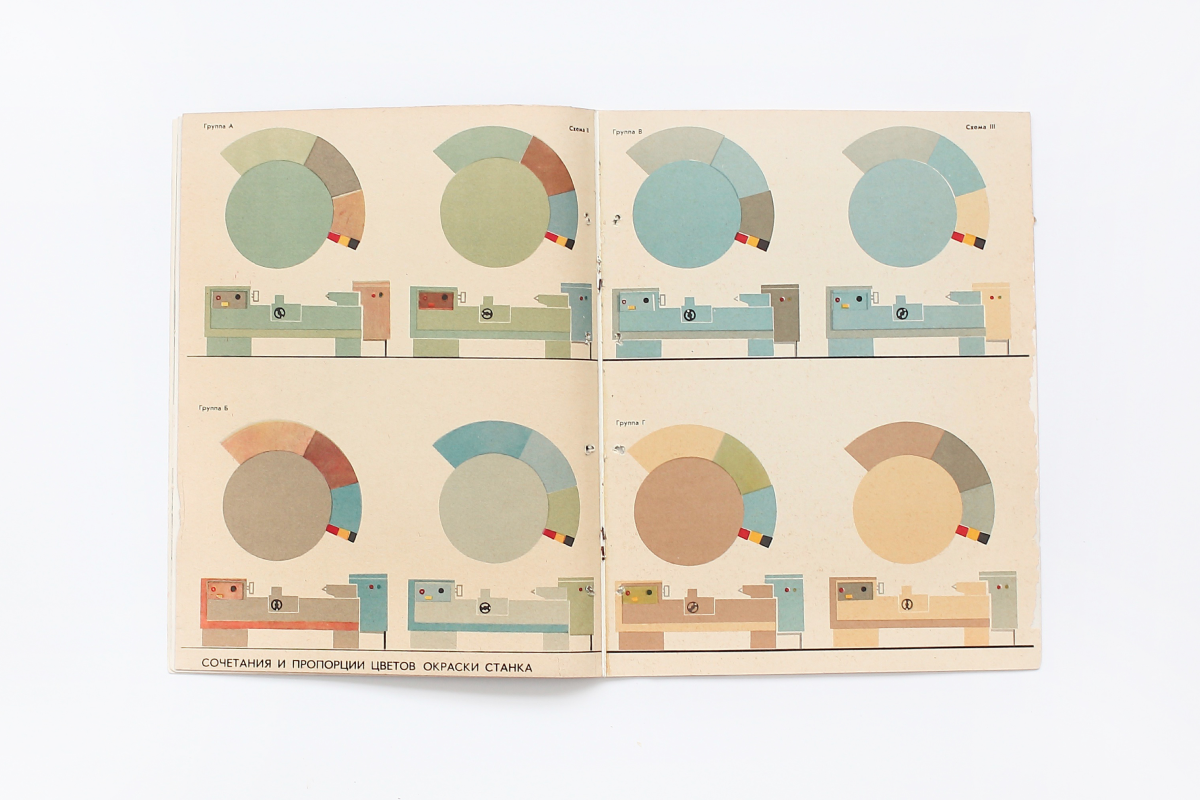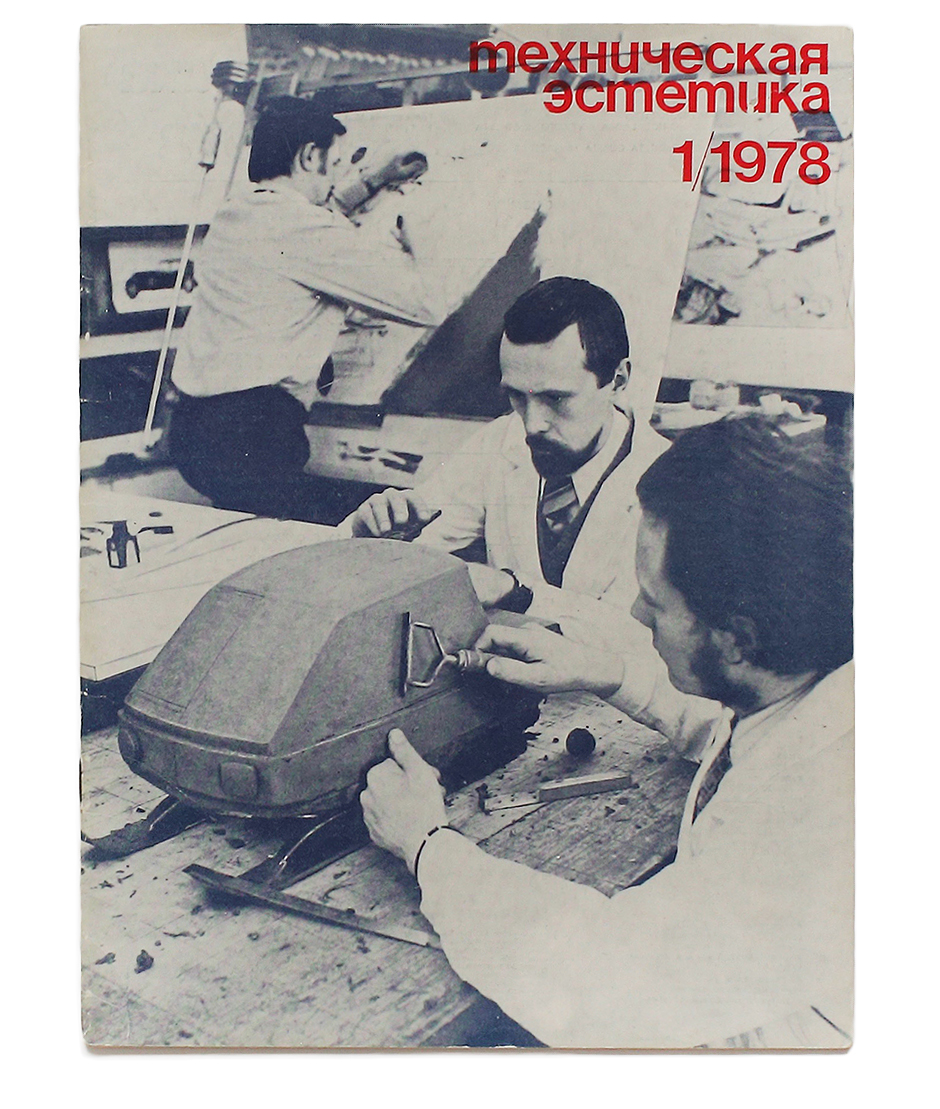
Техническая эстетика: эпизоды из жизни легендарного бюллетеня
ы живём во вре­ме­на, пе­ре­на­сы­щен­ные ин­фор­ма­ци­ей, но при этом очень мно­гое про­хо­дит ми­мо на­ше­го вни­ма­ния. К при­ме­ру, со­вет­ский ди­зайн. «Зверь», до сих пор эк­зо­ти­че­ский и ма­ло­изу­чен­ный не толь­ко в ми­ре, но и в со­вре­мен­ной Рос­сии.
Ис­кус­ство­вед Сер­гей Се­ров как-то за­ме­тил: «В Со­вет­ском Со­ю­зе бы­ли ди­зай­не­ры, а ди­зай­на не бы­ло». Фра­за кра­си­вая, но мне ка­жет­ся, бы­ли и ди­зай­не­ры, и ди­зайн. Бы­ла це­лая ор­га­ни­за­ция, за­ни­ма­ю­ща­я­ся про­бле­ма­ми раз­ви­тия ди­зай­на, — Все­со­юз­ный на­уч­но-ис­сле­до­ва­тель­ский ин­сти­тут тех­ни­че­ской эсте­ти­ки (ВНИ­ИТЭ). Сто­ит от­ме­тить, что офи­ци­аль­но в Стра­не Со­ве­тов ино­стран­ное сло­во ди­зайн бы­ло за­ме­не­но дву­мя опре­де­ле­ни­я­ми: тех­ни­че­ская эсте­ти­ка от­ве­ча­ла за те­о­рию, ху­до­же­ствен­ное кон­стру­и­ро­ва­ние за прак­ти­ку, а лю­ди, за­ни­ма­ю­щи­е­ся ди­зай­ном, на­зы­ва­лись ху­дож­ни­ка­ми-кон­струк­то­ра­ми. Не­ко­то­рые ви­дят в этом про­яв­ле­ние цен­зу­ры, но нуж­но пред­ста­влять се­бе то­гдаш­нюю си­ту­а­цию. В эпо­ху идео­ло­ги­че­ско­го про­ти­во­сто­я­ния двух си­стем — за­пад­ной и со­вет­ской — в стра­не стре­ми­лись опи­рать­ся на «своё», и не­уди­ви­тель­но, что это ка­са­лось и тер­ми­нов. Впро­чем, и сло­во «ди­зайн» ча­сто упо­треб­ля­лось в са­мой «Тех­ни­че­ской эсте­ти­ке», на стра­ни­цах жур­на­ла «Де­ко­ра­тив­ное ис­кус­ство» и в спе­ци­а­ли­зи­ро­ван­ной ли­те­ра­ту­ре.
Еле­на Чер­не­вич, ав­тор кни­ги «Гра­фи­че­ский ди­зайн в Рос­сии», так опи­сы­ва­ла воз­ник­ший в на­ча­ле 60-х не­обыч­ный ин­сти­тут:
Вда­ли от цен­тра Моск­вы, на тер­ри­то­рии ВД­НХ, где рас­по­ла­гал­ся ин­сти­тут, воз­ник то­гда остро­вок про­фес­си­о­наль­ной жиз­ни, пол­ной при­ви­ле­гий: в го­ды то­таль­ной изо­ля­ции от за­пад­ной куль­ту­ры здесь от­кры­лась воз­мож­ность ра­бо­тать в сре­де, на­сы­щен­ной ин­фор­ма­ци­ей и раз­го­во­ра­ми о со­вре­мен­ном ди­зай­не, ис­кус­стве, ар­хи­тек­ту­ре, мо­де.
Огром­ную роль сы­грал на­чаль­ный, ро­ман­ти­че­ский пе­ри­од, при­мер­но меж­ду 1964 и 1968 го­да­ми, ко­гда ин­сти­тут свёл вме­сте не­за­у­ряд­ных лю­дей раз­ных про­фес­сий. Ис­то­рик А. До­ро­гов, ис­кус­ство­ве­ды Л. Жа­до­ва и И. Го­лом­шток, фи­ло­соф К. Кан­тор, пси­хо­ло­ги В. Зин­чен­ко и М. Боб­не­ва, те­о­ре­тик де­я­тель­но­сти Г. Щед­ро­виц­кий и со­всем мо­ло­дые В. Зен­ков, ху­дож­ник-мыс­ли­тель, и те­о­ре­ти­ки-ме­то­до­ло­ги О. Ге­ни­са­рет­ский и В. Гла­зы­чев. Ин­тел­лек­ту­аль­ный по­тен­ци­ал, на­прав­лен­ный на по­зна­ние сфе­ры ди­зай­на, был столь вы­сок, что не­воль­но фор­ми­ро­ва­лось мак­си­ма­лист­ское и иде­а­ли­зи­ро­ван­ное пред­став­ле­ние о ди­зай­не как о куль­ту­ро­со­зи­да­ю­щей, де­мо­кра­ти­че­ской де­я­тель­но­сти — па­на­цее от всех бед. В сре­де прак­ти­ков ди­зай­на — те же умо­на­стро­е­ния.
Ди­зай­не­ры-гра­фи­ки по­гру­зи­лись в мир форм и об­ра­зов со­вре­мен­ной за­пад­ной прак­ти­ки, учи­лись ви­деть, «что та­кое хо­ро­шо» в гра­фи­че­ском ди­зай­не и по­ни­мать, как имен­но это «хо­ро­шо» по­лу­чи­лось. Во ВНИ­ИТЭ про­шли выс­шую шко­лу гра­фи­че­ско­го ди­зай­на не­сколь­ко че­ло­век: Вик­тор Зен­ков, Игорь Бе­ре­зов­ский, Алек­сандр Ер­мо­ла­ев, Ев­ге­ний Бо­гда­нов, Ва­ле­рий Чер­ни­ев­ский, Ра­миз Гу­сей­нов, Ири­на Ма­мон­то­ва.
Так как ВНИ­ИТЭ был един­ствен­ной ор­га­ни­за­ци­ей, от­ве­ча­вшей за ди­зайн, то в его функ­ции вхо­ди­ла и про­па­ган­да это­го но­во­го яв­ле­ния. И ин­сти­тут на­чал из­да­вать ин­фор­ма­ци­он­ный бюл­ле­тень — «Тех­ни­че­ская эсте­ти­ка». В ян­ва­ре 1964 го­да в свет вы­хо­дит пер­вый но­мер, а спу­стя два де­ся­ти­ле­тия он по­лу­чает ста­тус жур­на­ла (с 1983 го­да). На про­тя­же­нии все­го вре­ме­ни, ис­клю­чая по­след­ние два го­да су­ще­ство­ва­ния жур­на­ла, его глав­ным ре­дак­то­ром был ди­рек­тор ин­сти­ту­та Юрий Бо­ри­со­вич Со­ло­вьёв (по­след­ние го­ды ре­дак­цию воз­глав­лял Лев Алек­сан­дро­вич Кузь­мичёв).
1960-е: пер­вые но­ме­ра
В сво­их вос­по­ми­на­ни­ях Юрий Со­ло­вьёв пи­шет: «1 ян­ва­ря 1964 го­да вы­шел пер­вый но­мер бюл­ле­те­ня „Тех­ни­че­ская эсте­ти­ка“ ти­ра­жом 7000 эк­зем­пля­ров. Он про­из­вел впе­чат­ле­ние на ру­ко­во­ди­те­лей боль­шин­ства ми­ни­стерств и ве­домств, ку­да я его ра­зо­слал, и, ко­неч­но, на на­чаль­ство Ко­ми­те­та по на­у­ке и тех­ни­ке.<…> Бюл­ле­тень ВНИ­ИТЭ ра­зи­тель­но от­ли­чал­ся от при­ми­тив­но­го бюл­ле­те­ня, ко­то­рый из­да­вал сам ко­ми­тет. Вско­ре наш бюл­ле­тень при­об­рёл по­пу­ляр­ность и пре­вра­тил­ся в жур­нал с ти­ра­жом 38 ты­сяч эк­зем­пля­ров, в чём не­ма­лая за­слу­га за­ме­сти­те­ля глав­но­го ре­дак­то­ра Жан­ны Фе­до­се­е­вой и поз­же сме­нив­шей её Свет­ла­ны Силь­ве­стро­вой».
Пер­вые два го­да об­лож­ки бюл­ле­те­ня стро­и­лись по ша­бло­ну и пред­став­ля­ли со­бой «ко­стюм в по­ло­соч­ку» (и не­спро­ста, как мы уви­дим да­лее) с ме­ня­ю­щи­ми­ся от­тен­ка­ми. Ис­кус­ство­вед Вла­ди­мир Па­пер­ный (то­же ра­бо­тав­ший во ВНИ­ИТЭ) так опи­сы­ва­ет пер­вое впе­чат­ле­ние от жур­на­ла:
«Тех­ни­че­ская эсте­ти­ка» бы­ла лу­чом све­та в тём­ном цар­стве. Где-то в 62-м го­ду я уви­дел в ки­ос­ке сре­ди кра­си­вых, из­вест­ных и по­нят­ных нам жур­на­лов жур­нал с ка­кой-то се­рой об­лож­кой, с мел­ким шриф­том. Эта «ди­зай­нер­ская» об­лож­ка вос­при­ни­ма­лась как за­мор­ский зверь, как что-то не­слы­хан­ное, вещь, по­пав­шая сю­да с Мар­са…
В тот пе­ри­од те­мы вы­пус­ков осве­ща­ли со­зда­ние ин­те­рье­ра, про­ек­ти­ро­ва­ние упа­ков­ки, об­зор и ана­лиз опы­та за­ру­беж­ных фирм, рас­смот­ре­ние гра­фи­ки то­вар­ных и фир­мен­ных зна­ков, од­на­ко крас­ной ли­ни­ей про­хо­ди­ла те­ма стан­ко-, при­бо­ро- и ма­ши­но­стро­е­ния — то­го, что сей­час при­ня­то на­зы­вать про­мыш­лен­ным ди­зай­ном. На долж­но­сти ху­до­же­ствен­но­го ре­дак­то­ра сме­ни­лось не­сколь­ко че­ло­век: Н. Силь­ни­ков, А. Алё­шин, Е. Ре­бров, но основ­ным был Ни­ко­лай Стар­цев (1964–1965).
Про­хо­дя в 1966 го­ду во ВНИ­ИТЭ пред­ди­плом­ную прак­ти­ку, сту­дент Мо­сков­ско­го по­ли­гра­фи­че­ско­го ин­сти­ту­та Ва­си­лий Ва­ле­ри­ус (в даль­ней­шем книж­ный и те­ат­раль­ный ху­дож­ник) пред­ло­жил из­ме­нить ло­го­тип и прин­ци­пи­аль­но пе­ре­ра­бо­тал ма­кет бюл­ле­те­ня — по­ме­нял фор­мат с пря­мо­уголь­но­го на по­чти квад­рат­ный, а ло­го­тип стал пи­сать­ся строч­ны­ми бук­ва­ми. Для это­го был вы­бран но­вый (на тот мо­мент) шрифт — Гель­ве­ти­ка, ко­то­рый поль­зо­ва­лся то­гда боль­шой по­пу­ляр­но­стью у ху­дож­ни­ков-офор­ми­те­лей. Это бы­ла ру­си­фи­ци­ро­ван­ная вер­сия шриф­та Нойе Ха­ас Гро­теск Мак­са Ми­дин­ге­ра и Эду­ар­да Хоф­ма­на, ко­то­рую спро­ек­ти­ро­ва­ли Юрий Кур­ба­тов и Мак­сим Жу­ков, то­же сту­ден­ты Мо­сков­ско­го по­ли­гра­фи­че­ско­го ин­сти­ту­та.
Ла­ри­са Ва­си­льев­на Де­ни­сен­ко — ху­дож­ник-кон­струк­тор (ди­зай­нер), книж­ный гра­фик. Окон­чи­ла Мо­сков­ское выс­шее ху­до­же­ствен­но-про­мыш­лен­ное учи­ли­ще (бу­ду­щее им. Стро­га­но­ва). Свой твор­че­ский путь на­ча­ла в дет­ском фи­зи­ко-ма­те­ма­ти­че­ском жур­на­ле «Квант». Один из ве­ду­щих ди­зай­не­ров-гра­фи­ков ВНИ­ИТЭ, с 1984 по 1989 го­д бы­ла глав­ным ху­дож­ни­ком «Тех­ни­че­ской эсте­ти­ки». С 1997 по 2002 го­д ра­бо­та­ла арт-ди­рек­то­ром из­да­тель­ства «Арт-род­ник». В на­сто­я­щее вре­мя ра­бо­та­ет с раз­лич­ны­ми из­да­тель­ства­ми и му­зе­я­ми как сво­бод­ный ху­дож­ник.